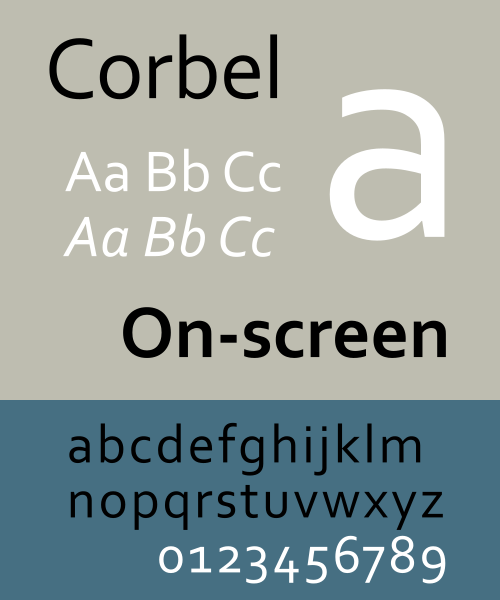
| カテゴリ | サンセリフ |
| 分類 | ヒューマニスト |
| デザイナー | ジェレミー・タンカード |
| 鋳造所 | マイクロソフト |
| リリース日 | 2004 |
Corbel は、 MicrosoftのためにJeremy Tankardがデザインしたヒューマニスト サンセリフ 書体です。これは、 Windows Vistaでリリースされたさまざまなデザイナーによるフォント スイートであるClearType フォント コレクションの一部です。すべてCで始まるのは、Microsoft のClearTypeテキスト レンダリング システム (LCD モニターでテキストを明瞭に読み取れるように設計されたテキスト レンダリング エンジン)で適切に動作するように設計されていることを示しています。同じグループには、他にCalibri、Cambria、Candara、Consolas、Constantia のフォントもあります。
デザイン
Corbel の使用に関する宣伝文句では、「画面上ですっきりとした見栄えになるよう設計されています。文字の形はオープンで、柔らかく流れるような曲線を描いています。小さいサイズでは読みやすく明瞭です。大きいサイズでは、形状のディテールとスタイルがより顕著になります。」と説明されています。イタリック体は真のイタリック体で、セリフ体やカリグラフィの影響を受けており、多くの文字に右向きの尾が付いています。デザインの多くの側面は、同じくヒューマニストのサンセリフ体である Calibri や Candara に似ています。これらと同様に、平均よりもわずかに凝縮されています。フォントデザイナーのRaph Levien は、Typographicaで Corbel をレビューし、 Frutigerに似ていると述べました。[1] Tankard は、このファミリーのデザインの狙いを次のように説明しています。「最近よく見かける丸い i-dot sans フォントから脱却したかったのです。かわいらしさよりも、もっと主張のあるものにしたいと思いました。」私は傾斜したローマン体ではなく、イタリック体を表現力豊かにしたかったのです。」[2]
Corbel はデフォルトで数字をテキスト数字(旧スタイルまたは小文字の数字) としてレンダリングします。これは、数字を本文に組み込む場合に好まれます。これは、特に画面に表示するように設計されたサンセリフ書体では珍しい選択ですが、他の ClearType フォントのいくつかでもこれがデフォルトのオプションになっています。OpenTypeのスタイル代替メニューまたはCSS を使用して、数字の並びを提案できます。テキスト数字は、Microsoft のセリフ Georgia書体
にも見られます。font-variant-numeric:lining-nums